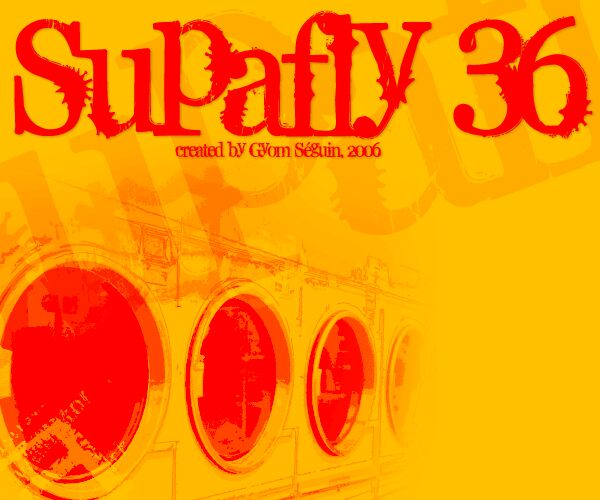
Supafly 36, di Gyomsegs, è un font display gratuito dallo stile distressed, con un aspetto graffiato e rovinato che richiama sia i poster vittoriani che le vecchie stampe artigianali. Le lettere mescolano forme alte e classiche con bordi sfrangiati e segni grezzi, che rendono la silhouette dinamica anziché uniforme.
È perfetto per flyer musicali, grafiche a tema Halloween, copertine di fanzine, etichette e titoli dove un tocco di sporcizia contribuisce a creare l'atmosfera giusta. Essendo un font gratuito, funziona bene anche per titoli brevi, bozzetti di loghi e capolettera, poiché i suoi contorni strappati e le forme stravaganti comunicano immediatamente il messaggio.